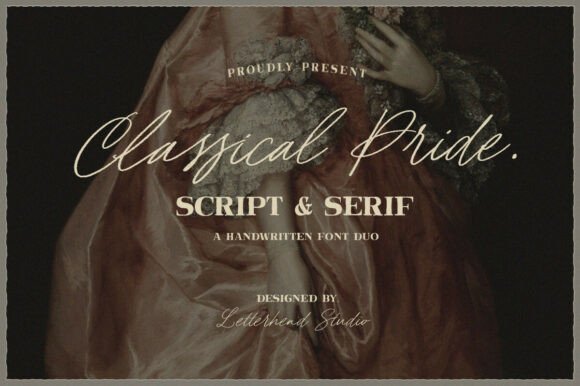
Classical Pride Duo Font
การค้นหาองค์ประกอบการออกแบบที่เหมาะสมอาจเป็นเรื่องท้าทาย แต่ Classical Pride Duo Font นำเสนอคอลเลกชันที่โดดเด่นซึ่งช่วยยกระดับงานของคุณได้ทันที
ไม่ว่าคุณจะสร้างผลิตภัณฑ์ POD (Print on Demand) คำเชิญงานแต่งงาน หรือกราฟิกโซเชียลมีเดีย Classical Pride Duo Font ก็เหมาะสมอย่างยิ่ง